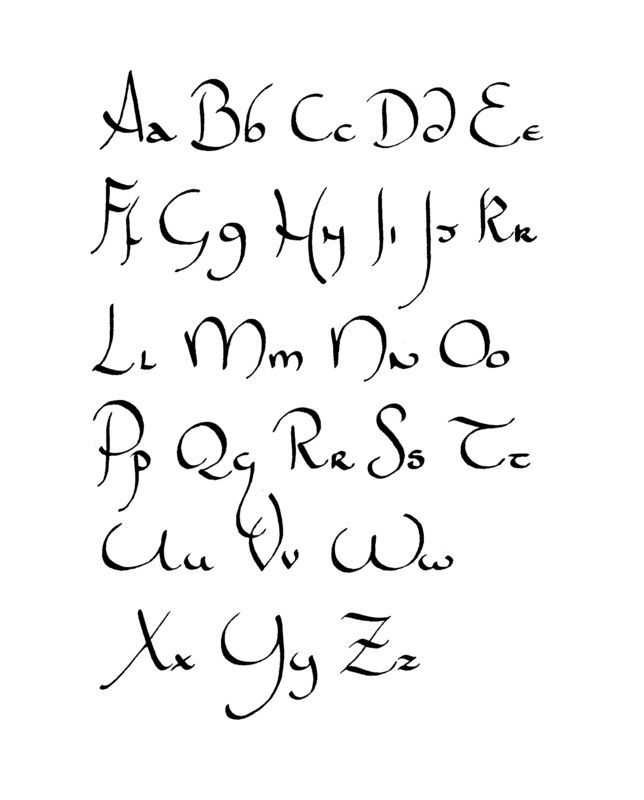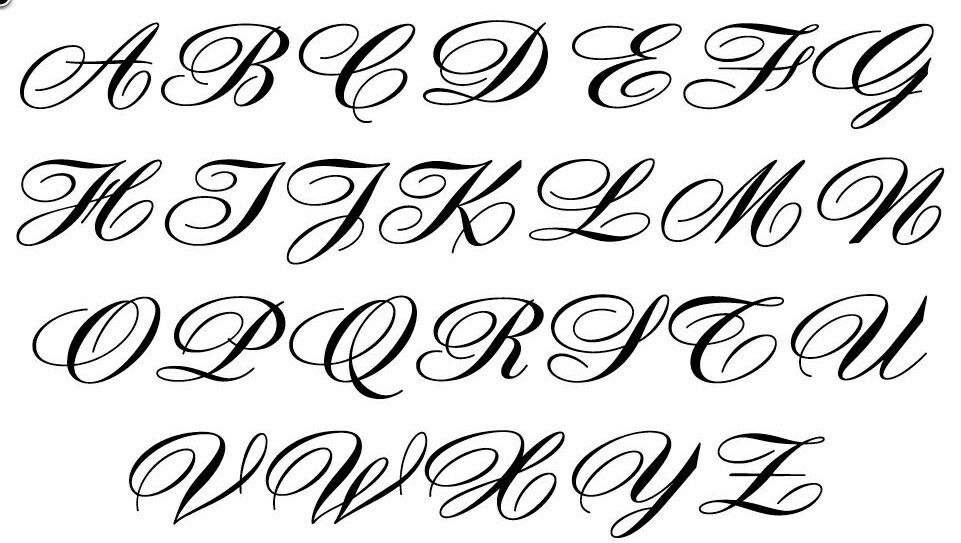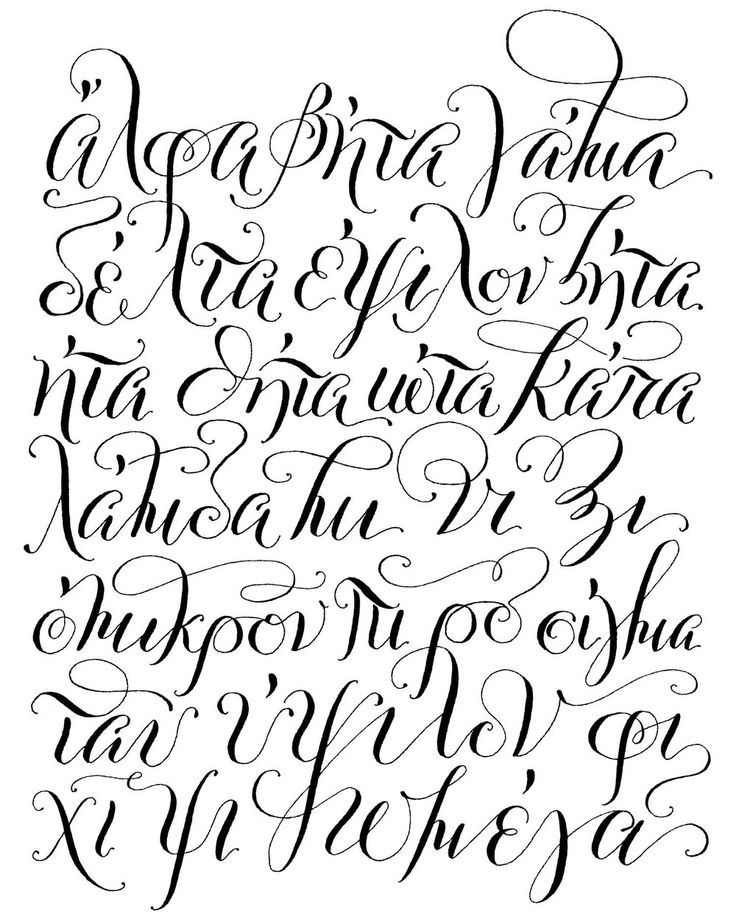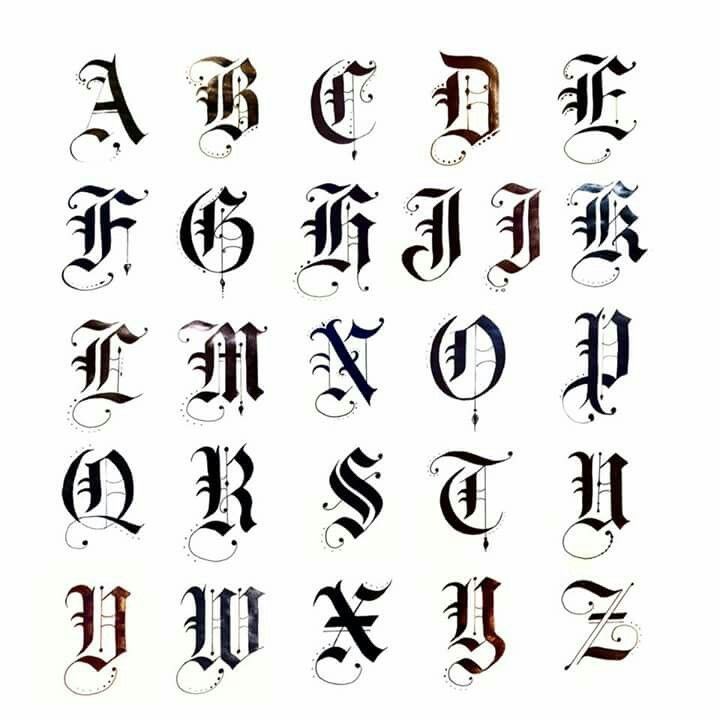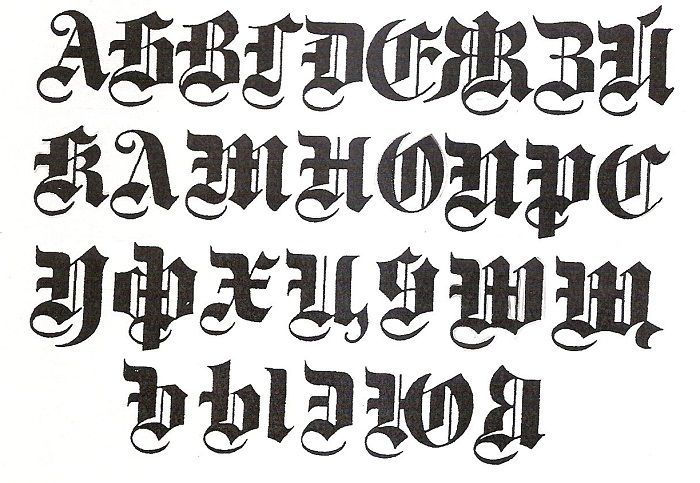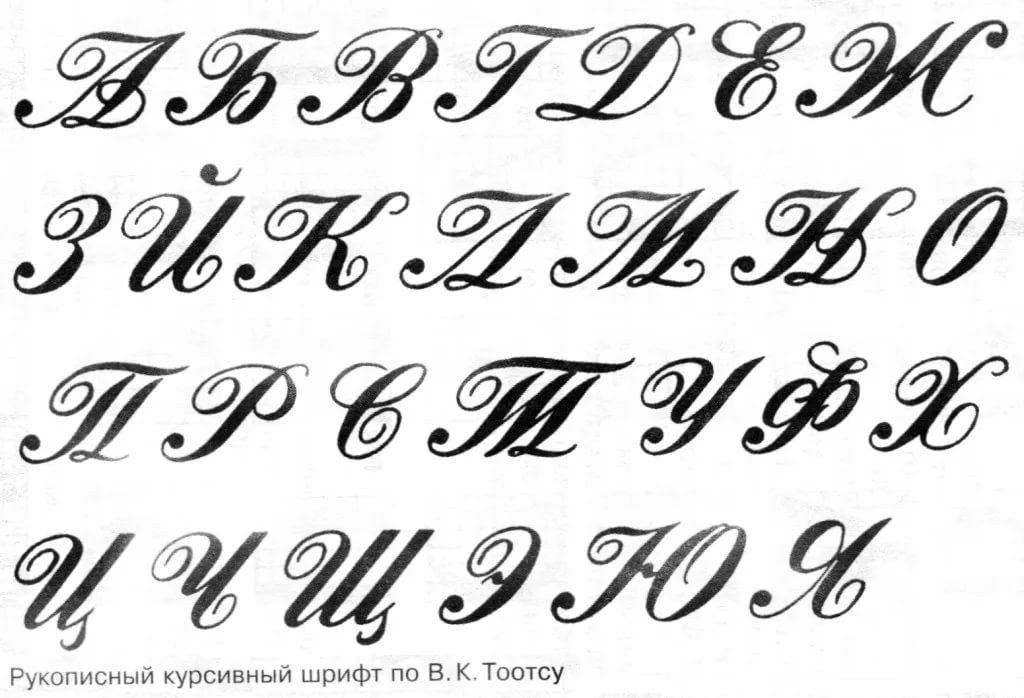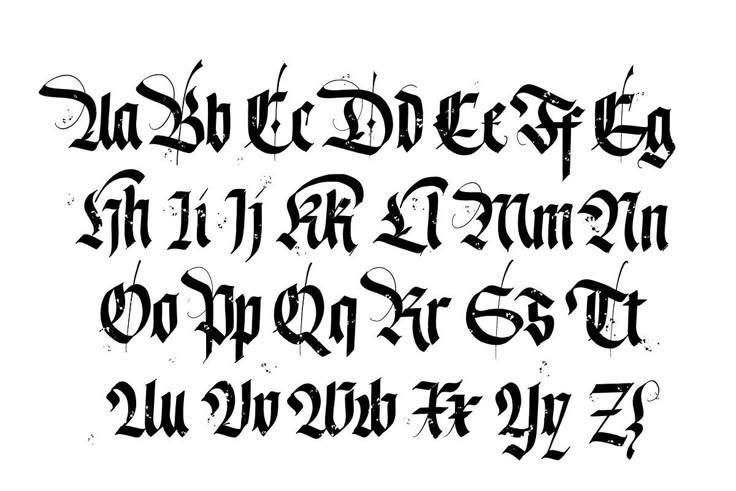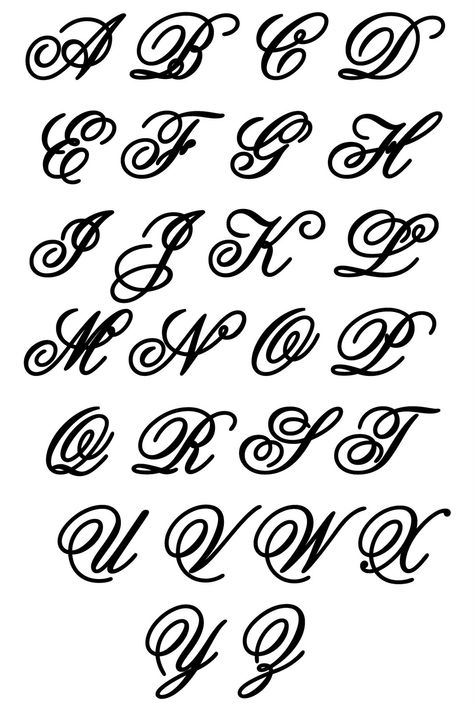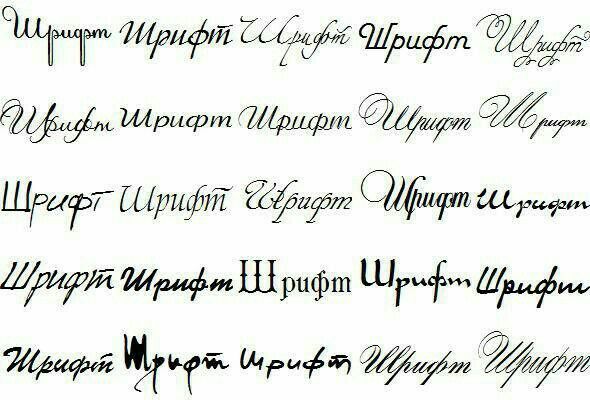
Тестовые татуировки на сегодняшний день пользуются огромной популярностью и являются наиболее востребованным направлением в нательном рисунке. Особенно ими увлекаются молодые люди, которым важно не только быть в тренде, но и заявить окружающему миру о своей уникальности и значимости.
Шрифты для тату онлайн подбор по картинкам: виды шрифтов
И девушки, и парни испытывают особый интерес к изречениям, известным или не очень, на философские тематики, а также вечную любовную тему. В большинстве случаев для татуировки выбирают текст на английском языке или на латыни, хотя некоторые ищут шрифты для тату, используя онлайн подбор на русском языке.
От чего зависит уникальность татуировки?
Чтобы украсить себя красивой и оригинальной татуировкой, нанесенной на плечо, запястье или щиколотку, важно не только найти высказывание, которое наилучшим образом передает вашу сущность и ваши личные убеждения, но и выбрать подходящий шрифт.
Качество надписи и ее внешний вид во многом зависит от удачного шрифта, поэтому не стоит пускать это дело на самотек, а лучше воспользоваться такой услугой, как.
Как выбрать «свой» шрифт?
К вопросу выбора шрифта стоит отнестись ответственно, поскольку именно от него зависит, насколько эффектно и уместно будет смотреться надпись, будет ли она привлекать взгляды окружающих или вызывать плохо скрываемое недоумение. Все шрифты для тату (онлайн подбор бесплатно ) обладают неповторимыми формами и своим размером. Уникальными их делает толщина линии, расстояние между буквами, градус наклона и еще много других характеристик.
Как выбрать «свой» шрифт?
Нанесение татуировки – решение серьезное, ведь подразумевается, что вы будете носить ее до конца жизни, поэтому не стоит спешить, и прежде чем отправляться в тату-салон, стоит провести немного времени за компьютером и найти то, что вам понравиться. Чтобы надпись удалась, следует вбить в поисковик простую фразу: и интернет выдаст вам сотни вариантов, один из которых вам особенно придется по душе, и будет соответствовать вашему стилю.
Чтобы мастер мог создать тату надпись так, чтобы вы не пожалели о том, что выбрали, принять правильное решение бывает весьма непросто. Тем боле, что татуировка является подтверждением вашей индивидуальности, а значит и стиль, в котором будет выполнена надпись, должен быть особенным.
Древние шрифты для татуировок на теле
Но как бы тяжело это не показалось на первый взгляд, нет ничего невозможного для того, кто задастся целью. Поэтому нужно рассмотреть все возможные варианты, оценить каждый, взвесив преимущества и недостатки. Кроме того, следует самому себе дать ответ на один простой вопрос: что именно вы хотите видеть на себе и готовы ли вы смотреть на это каждый день?
Каллиграфические шрифты
Самыми распространенными шрифтами в татуировке являются каллиграфические шрифты. Многие отдают предпочтение именно им потому, что у каждого человека есть свой индивидуальный почерк, использование которого уже само по себе является оригинальным дизайнерским решением.
Каллиграфические шрифты бывают разными: от классического до написанного от руки.
Каллиграфические шрифты
Рукописные шрифты для тату подыскать поможет онлайн подбор . Надпись, выполненная с использованием рукописного шрифта, будет неповторимой и всегда актуальной. Не стоит забывать, что лишняя черточка, размер слова или наклон буквы, не говоря уже о дополнительных элементах, завитках, узорах и т.д. может повлиять на общую картинку и даже на восприятие смысла.
Готический шрифт
Фанатам готического стиля принимать решение относительно выбора шрифта намного легче, ведь они редко когда изменяют своим убеждениям. Этот шрифт может быть простым или сложным, поэтому при выборе стоит убедиться, что надпись можно будет легко прочесть, если вы конечно не пытаетесь создать замысловатое, сложное для расшифровки начертание.
Западный шрифт на теле у девушки
Найти шрифт, который по стилистике соответствует традициям Дикого Запада в тату — салоне или в интернете не составит особого труда.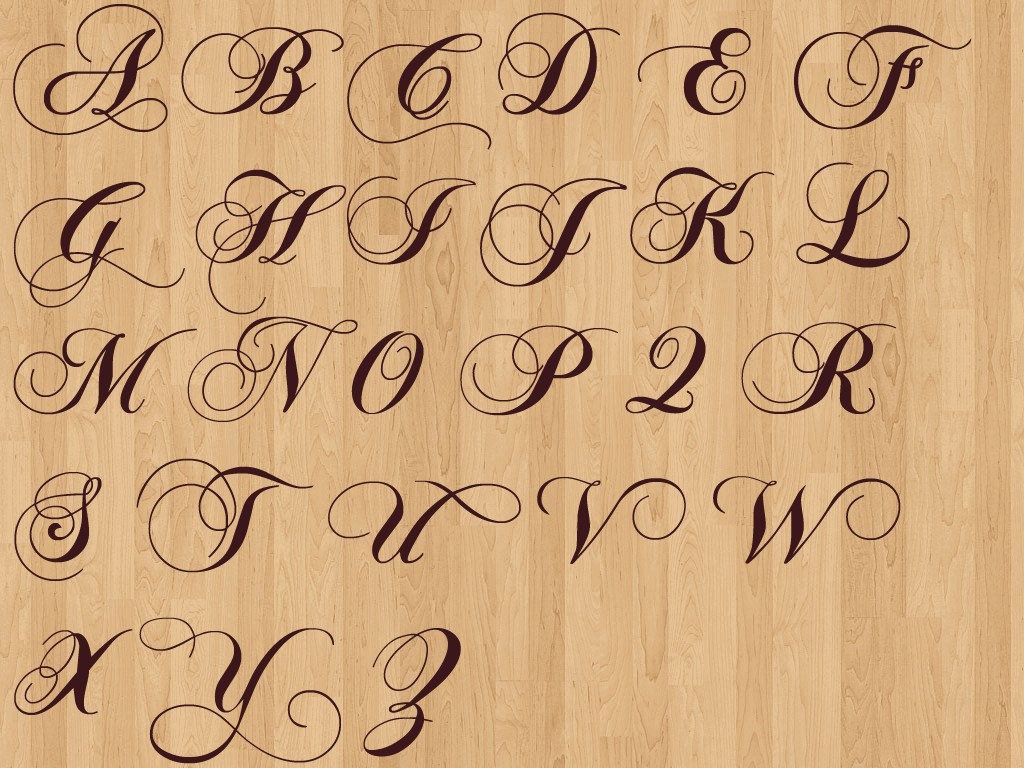
Западный шрифт на теле у девушки
Особой популярностью он пользуется среди байкеров, а также сильных, уверенных в себе, подчас даже брутальных мужчин, которые считают такой стиль наилучшим отображением свой сути, и использую его для надписей на логотипах, или для нанесения инициалов.
Азиатские шрифты
Азиатские шрифты используют те, кто хочет выделиться из толпы и претендует на звание загадочной личности. В азиатском или арабском стиле может быть выполнена и надпись на родном языке, стилизованная под письменность восточных народов.
Шрифт, в стиле пишущей машинки
Надписи, сделанные стилем старых пишущих машинок сегодня на пике популярности. Благодаря тому, что шрифт часто сопровождается различными дефектами, надпись получается действительно уникальной и неповторимой, что вызывает особый интерес.